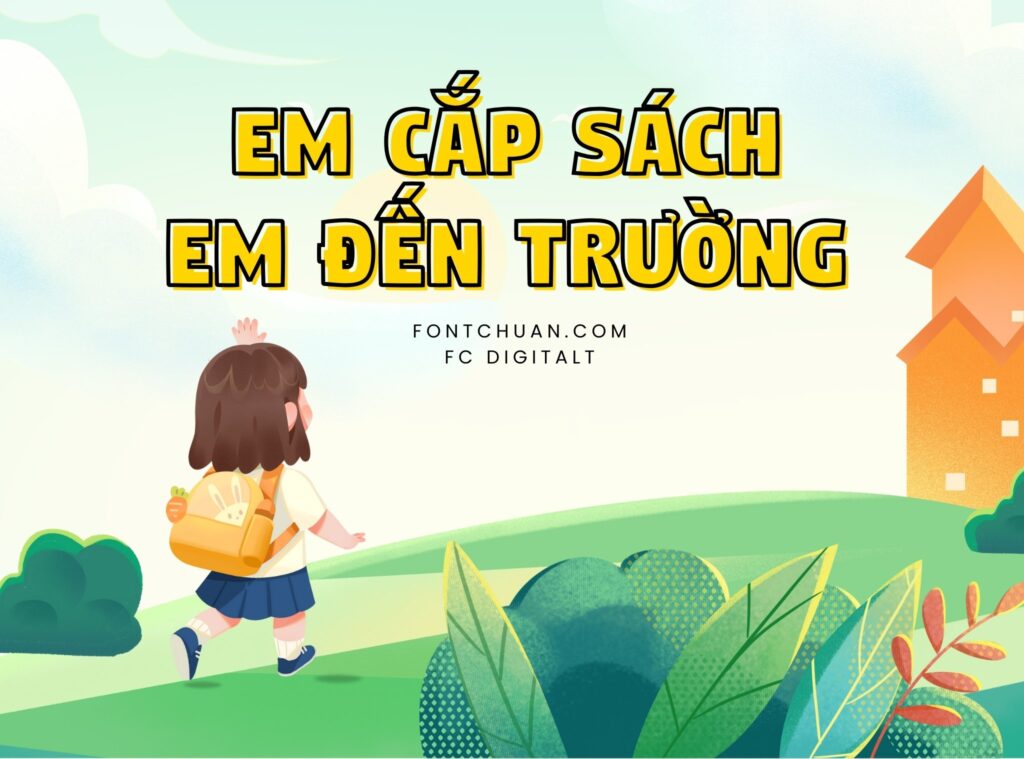
Digitalt là một kiểu chữ sans serif nổi bật, được thiết kế bởi Grzegorz Luk. Font này mang phong cách hiện đại với các đường nét đậm và cấu trúc chữ cân đối, tạo nên sự thu hút và dễ đọc cho người xem. Với tính linh hoạt cao, Digitalt có thể được sử dụng như một Font Lễ hội để trang trí các ấn phẩm vui tươi, sôi động, hoặc trở thành font ngày nhà giáo Việt Nam trong các thiết kế chúc mừng, thiệp và poster dành riêng cho ngày lễ đặc biệt này. Digitalt hỗ trợ 57 ngôn ngữ, giúp nhà thiết kế tiếp cận đa dạng đối tượng người dùng.
Phiên bản Việt hóa FC Digitalt do Font Chuẩn thực hiện chia sẻ hoàn toàn miễn phí, mang lại sự tiện lợi cho cộng đồng thiết kế Việt Nam.
Với cấu trúc to tròn, thiết kế mạnh mẽ và hiện đại, FC Digitalt phù hợp cho nhiều mục đích sử dụng như thiết kế logo, tiêu đề, poster, bao bì sản phẩm, đặc biệt là ứng dụng đồ họa cho thiếu nhi và các ấn phẩm quảng cáo khác.